Tiff, la herramienta online que permite comparar tipografías
Las variaciones tipográficas, por ínfimas que puedan parecer, influyen y pueden cambiar por completo un diseño.
No es difícil darse cuenta de las evidentes diferencias entre una tipografía manuscrita y una sin serifa. Sin embargo, muchas veces las semejanzas entre fuentes de un mismo estilo son más complicadas de revelar; especialmente para el ojo inexperto. El diseñador canadiense Mu Ye ha desarrollado Tiff, una web que permite comparar cuatro glifos de dos tipografías distintas de manera fácil y rápida.
Tan solo es necesario elegir la tipografía principal, que se mostrará en azul y con cuál la queremos comparar; esta opción se mostrará en rojo, superpuesta sobre a la primera. De esta manera, saltan a la vista las diferencias entre tipografías, por poco evidentes que pudiesen parecer a simple vista.
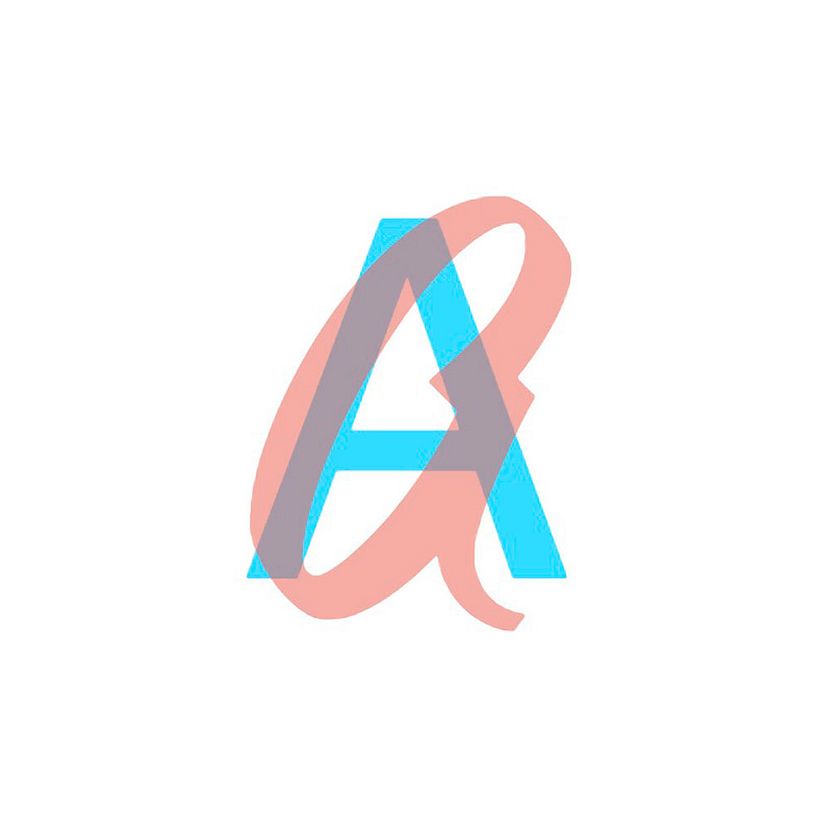
Pueden elegirse hasta cuadro glifos, en mayúsculas o minúsculas para compararlos al mismo tiempo, basta con escribirlos en las cajas dispuestas al pie de la página. Tiff funciona con Google Fonts, lo que quiere decir que pueden elegirse cualquiera de las tipografías de su catálogo, así como las tipografías propias del sistema.
Tiff, una herramienta básica y sencilla para comparar tipografías online.